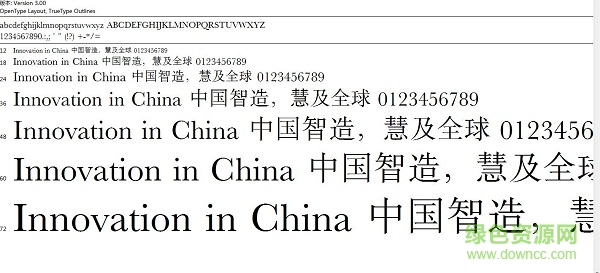
msung是什么字體?msung字體就是蒙納宋體,勻稱美觀,比例合度,視覺閱讀體驗良好,不容易視覺疲勞,一般用在報紙或是書刊的正文排版方面,喜歡就來綠色資源網(wǎng)下載吧!
msung字體筆畫橫平豎直,橫細(xì)豎粗,棱角分明,結(jié)構(gòu)嚴(yán)謹(jǐn),整齊均勻,有極強(qiáng)的筆畫規(guī)律性,從而使人在閱讀時有一種舒適醒目的感覺。